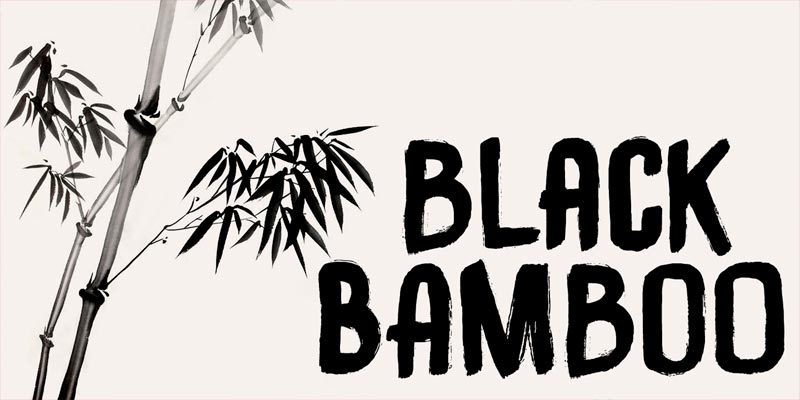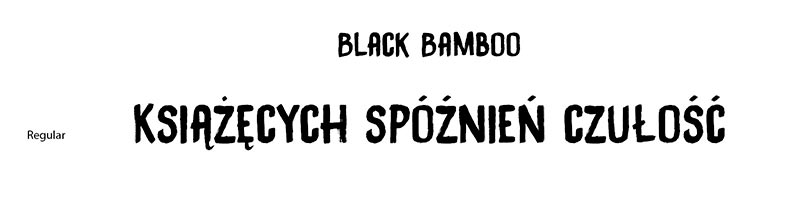
Font Black Bamboo
Black Bamboo to kolejny w naszym studiu font projektu Davida Kerkhoffa. Charakteryzuje się literami przypominającymi odręcznie malowane pismo.